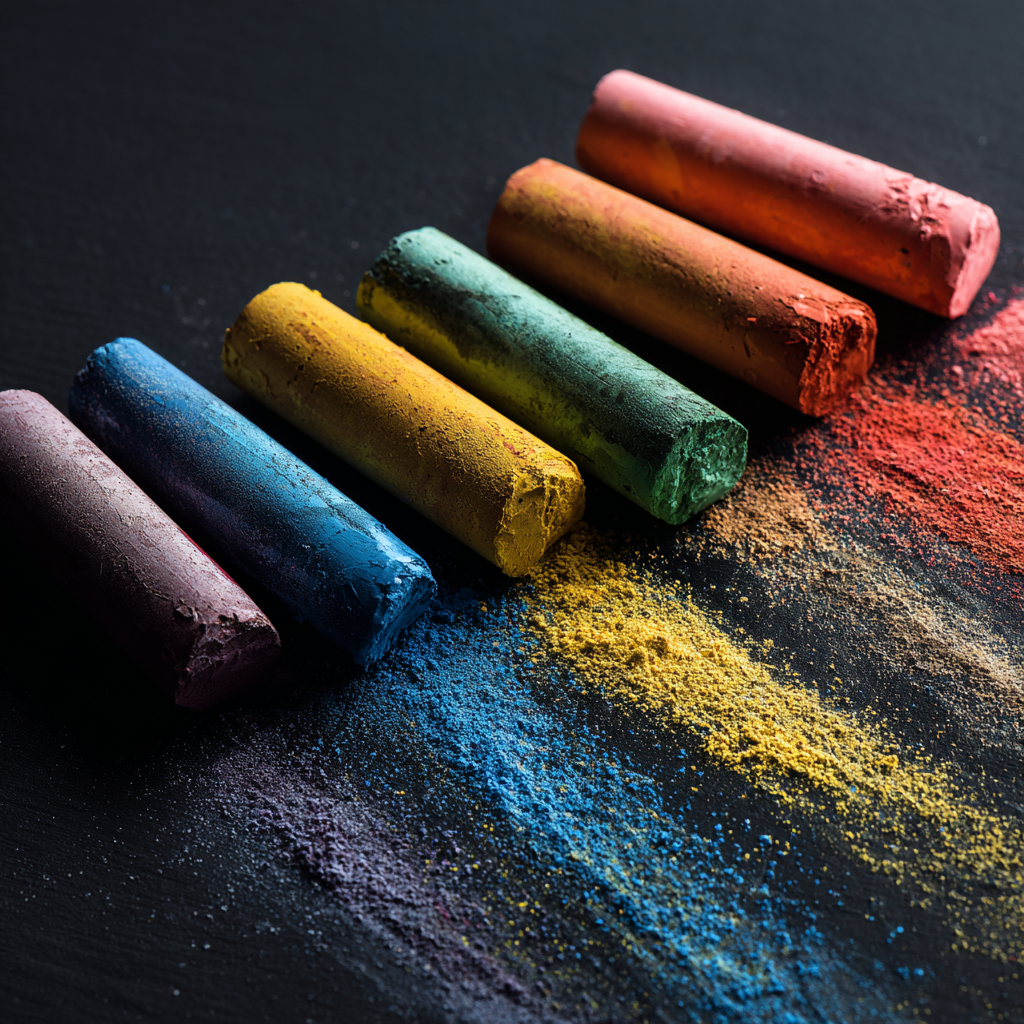
분필은 교실과 회의실에서 오랜 시간 동안 사용되어온 필기 도구예요. 최근에는 전자 칠판이나 빔프로젝터가 많아졌지만, 여전히 분필의 장점은 무시할 수 없어요. 글씨가 또렷하게 나오고, 직관적으로 내용을 전달하기에 정말 좋아요.
특히 판서를 자주 해야 하는 교사나 강사들에게는 어떤 분필을 쓰느냐, 어떻게 쓰느냐가 매우 중요하죠. 판서의 품질이 수업 전달력과 직결되기 때문이에요. 그래서 오늘은 분필의 특성과 사용법, 그리고 판서를 잘하는 실전 팁까지 전부 알려줄게요! ✍️
내가 생각했을 때 분필을 잘 다루는 능력은 단순히 글씨를 잘 쓰는 걸 넘어서 학생과의 소통 도구가 되는 거 같아요. 단단하지만 부드럽고, 지워지는 속성 덕분에 반복 학습에도 매우 유용하죠.😊
자, 이제 하나하나 자세히 살펴보면서 판서 고수로 거듭나보자구요!
✋ 분필 올바르게 잡는 법
분필을 잡는 자세는 판서의 질을 좌우하는 핵심 포인트예요. 많은 사람들이 펜처럼 분필을 끝까지 꽉 쥐고 쓰는데, 이건 오히려 손에 힘이 들어가면서 글씨가 부정확해지기 쉬워요. 분필은 펜보다 굵기와 질감이 다르기 때문에, 살짝 힘을 빼고 손끝에서 3cm 정도 위를 잡아주는 게 좋아요.
이때, 검지와 엄지로 가볍게 집고 중지를 받쳐주는 삼지법이 가장 안정적이에요. 손목과 팔꿈치는 너무 붙이지 말고, 자연스럽게 띄운 채로 움직이는 게 좋아요. 글씨가 흔들리지 않도록, 팔 전체를 써서 쓰는 느낌을 가져야 해요.
분필을 자주 부러뜨리는 경우, 힘을 과하게 주는 습관 때문일 수 있어요. 부드러운 압력으로 쓰면 손에도 무리가 가지 않고, 분필도 오래 사용할 수 있어요. 글씨가 연하게 나올 땐 분필 각도를 살짝 눕혀보세요.
또 하나의 팁은 분필의 끝을 깎는 것이에요. 뾰족한 형태로 만들면 세밀한 판서가 가능하고, 가는 글씨나 그림을 표현할 때 유리하답니다. ✍️
🧽 분필 잡는 법 비교표
잡는 방식 설명 추천 상황 삼지법 엄지+검지+중지로 안정적으로 잡는 방식 일반적인 판서 집게법 엄지와 검지만으로 가볍게 쥐는 방식 짧은 메모, 빠른 필기 눕혀 잡기 분필을 눕혀 넓게 쓰는 방식 강조, 큰 글씨 이렇게 다양한 잡는 방법을 상황에 따라 적용하면 손목도 덜 아프고, 글씨도 또렷하게 나올 수 있어요. 가볍고 정확한 필압이 포인트랍니다! 😉
🖍 판서할 때 글씨 잘 쓰는 팁
글씨를 잘 쓰려면 우선 크기와 간격에 집중해야 해요. 너무 작으면 뒷자리 학생이 보기 힘들고, 너무 크면 한 판에 많은 내용을 담기 어려워요. 글자 높이는 약 10~15cm 정도가 적당하고, 글자 간 간격은 2cm 내외가 좋아요.
문장 간 간격을 적절히 주면 칠판이 덜 답답해 보이고, 전달력도 확실히 좋아져요. 줄이 보이지 않는 칠판에서는 눈대중으로 수평을 맞추는 게 어렵지만, 눈높이 기준선을 잡고 쓰면 줄맞춤이 훨씬 쉬워진답니다.
글씨의 굵기는 일정하게 유지하는 것이 핵심이에요. 한 글자에서 두께가 달라지면 가독성이 떨어지기 때문이죠. 특히 획의 방향이 바뀔 때는 힘을 살짝 빼서 부드럽게 연결해주는 게 중요해요.
문장 강조가 필요할 때는 다른 색 분필을 활용해보세요. 예를 들어 중요한 개념은 빨간색, 예시는 초록색 등으로 나누면 학생들도 더 쉽게 이해할 수 있어요. 컬러 분필을 적절히 섞으면 시각적인 효과도 훌륭해요.🌈
📏 판서 구성 요소 요약표
항목 설명 적용 팁 글자 크기 10~15cm 정도가 적당 눈높이 기준으로 작성 간격 문장 간 2cm 이상 확보 답답함 방지, 강조 효과 강조 색상 또는 박스 활용 컬러 분필 활용 이런 세심한 요소들을 챙기면 누구나 판서의 달인이 될 수 있어요. 연습이 중요하니, 실제 칠판에 자주 써보면서 익히는 게 가장 좋아요! 🖍️
🧼 칠판 관리 및 분필 보관법
좋은 판서를 위해선 칠판 상태 관리도 꼭 필요해요. 칠판이 더럽거나 분필 가루가 많이 쌓이면 글씨가 번지거나 잘 안 보일 수 있어요. 수업 전에는 마른 천이나 칠판 전용 수건으로 전체를 깔끔하게 닦아주는 게 좋고, 물걸레는 수업 후에 사용하는 게 더 좋아요.
분필 가루가 많이 남는 경우엔 ‘저먼 분필’ 같은 저먼가루 제품을 쓰는 것도 추천이에요. 분필 종류에 따라 가루 발생량이 다르고, 칠판과의 마찰도 다르기 때문에 상황에 맞는 분필을 선택해야 해요.
분필은 습기와 충격에 약하기 때문에 보관도 신경 써야 해요. 종이 상자보다는 밀폐 플라스틱 용기나 틴케이스에 넣어두면 오래 쓸 수 있어요. 특히 여름철에는 실내 온도와 습도 조절도 중요해요.
지우개 역시 자주 세척해서 사용하면 지울 때 가루가 덜 날리고, 칠판도 깔끔하게 유지돼요. 지우개 안쪽에 모인 분필가루는 주기적으로 털어주는 습관이 필요하답니다. 😊
📚 효율적인 강의판서 방법
효율적인 판서를 위해선 전체적인 구조를 미리 머릿속에 그리는 게 중요해요. 칠판을 3등분하거나 4등분해서 '제목-내용-예시-정리'처럼 구성하면 보는 사람이 훨씬 이해하기 쉬워요. 이렇게 계획성 있는 판서는 수업의 흐름도 자연스럽게 해줘요.
중요한 개념은 항상 같은 위치에 쓰는 습관을 들이면 학생들이 익숙해지고 집중력이 높아져요. 예를 들어, 개념은 왼쪽 상단, 정리는 오른쪽 하단처럼 위치를 고정해두면 정보 정리에 큰 도움이 돼요.
색상 분필을 전략적으로 활용하는 것도 핵심이에요. 같은 정보라도 색이 다르면 눈에 더 잘 띄고 기억에 오래 남거든요. 글씨만 계속 쓴다고 능사가 아니라, '정보를 어떻게 시각적으로 정리하느냐'가 진짜 포인트예요.🧠
또한, 너무 많은 내용을 한 칠판에 다 넣으려고 하지 말고, 핵심만 쓰고 나머지는 구두 설명으로 보완하는 방식도 추천해요. 이는 집중도를 높이고, 칠판에 대한 부담도 줄여줘요.
Q1. 분필을 오래 쓰는 방법은 뭐가 있을까요?
A1. 분필을 눕혀서 부드럽게 사용하고, 케이스에 보관하면 훨씬 오래 쓸 수 있어요.
Q2. 판서할 때 손에 분필 가루 안 묻히는 법은?
A2. 분필 홀더를 사용하거나, 저먼가루 분필을 사용하면 가루 날림이 적어요.
Q3. 어떤 분필이 제일 잘 써지나요?
A3. 니시노야, 하크네오 같은 프리미엄 분필이 부드럽고 선명하게 써져요.
Q4. 판서용 글씨체 연습하는 팁은?
A4. 칠판에 격자무늬 테이프를 붙여 연습하면 정렬과 비율 감각이 좋아져요.
Q5. 판서 시 손이 덜 떨리는 방법은 있나요?
A5. 팔 전체로 움직이고 손목 힘을 빼면 떨림이 훨씬 줄어들어요.
Q6. 전자칠판과 분필칠판 중 뭐가 더 좋아요?
A6. 상황에 따라 달라요. 전자칠판은 자료공유에 좋고, 분필칠판은 직관적이고 집중도 높여줘요.
Q7. 분필 칠판이 너무 미끄럽게 느껴져요. 왜 그럴까요?
A7. 칠판 표면이 매끄럽거나 새 제품인 경우 그래요. 마른천으로 여러 번 닦아주면 좋아져요.
Q8. 칠판 청소는 얼마나 자주 해야 하나요?
A8. 매 수업 전후에 가볍게 닦고, 일주일에 한 번은 물걸레로 꼼꼼히 청소해주는 게 좋아요.